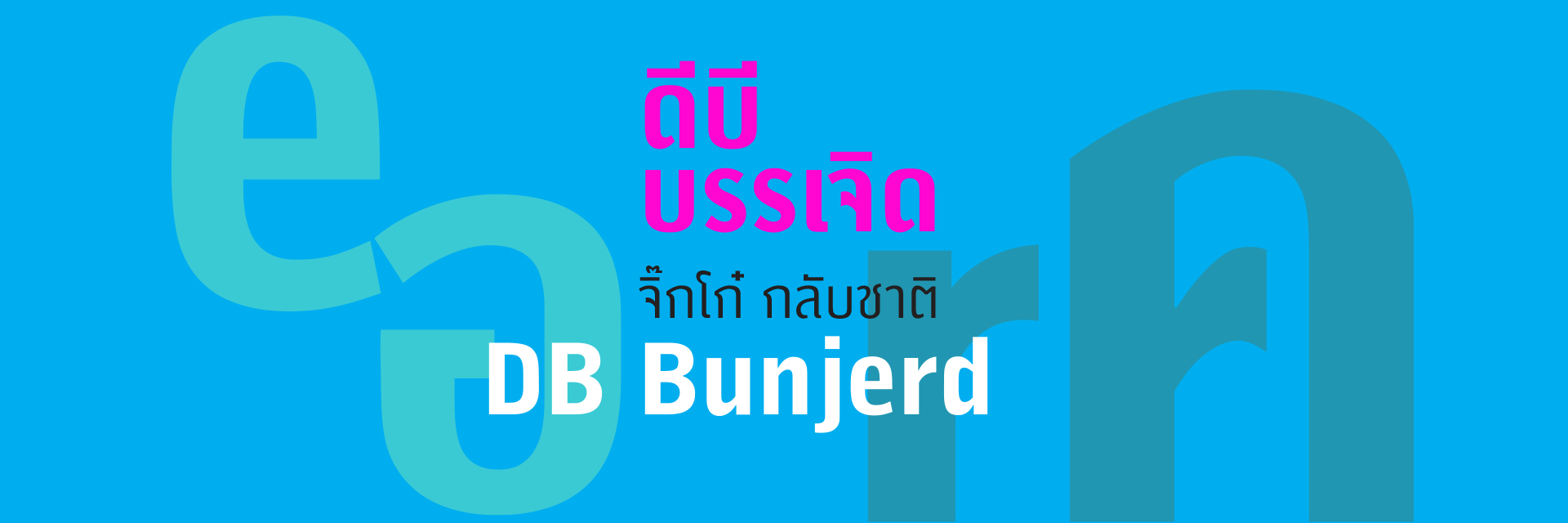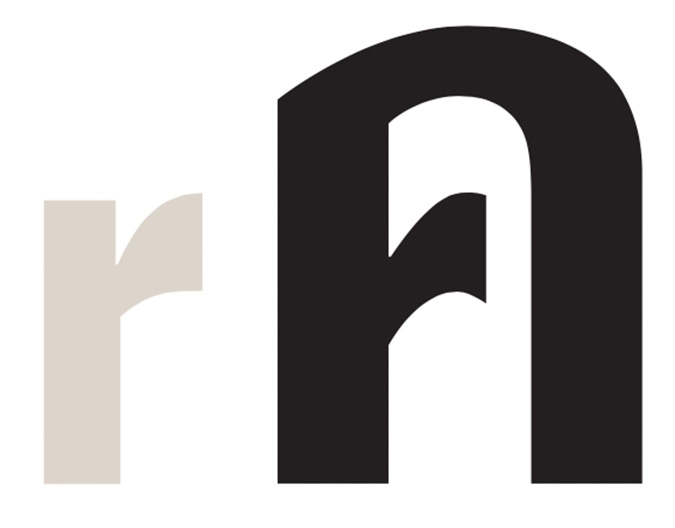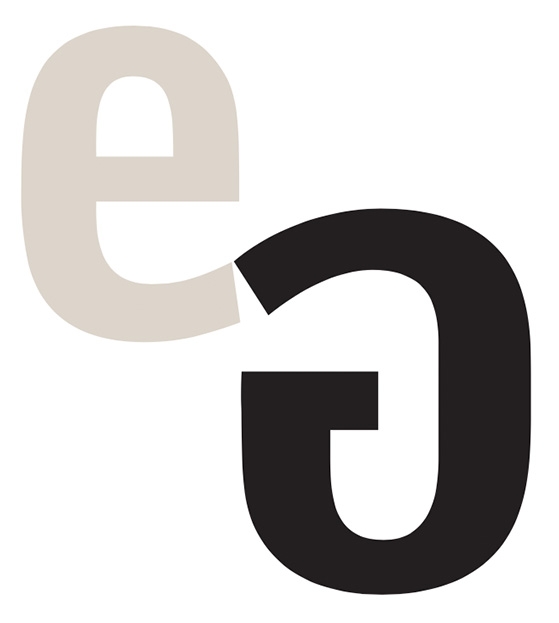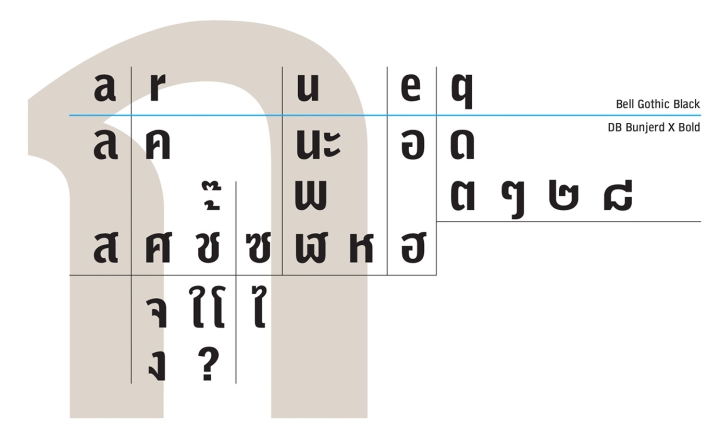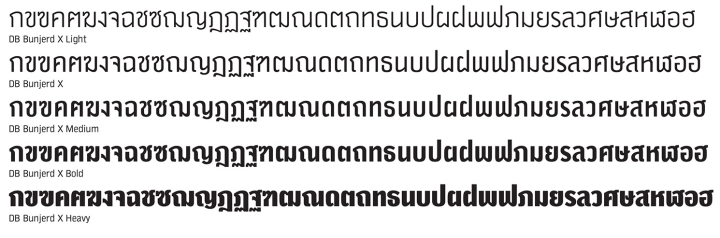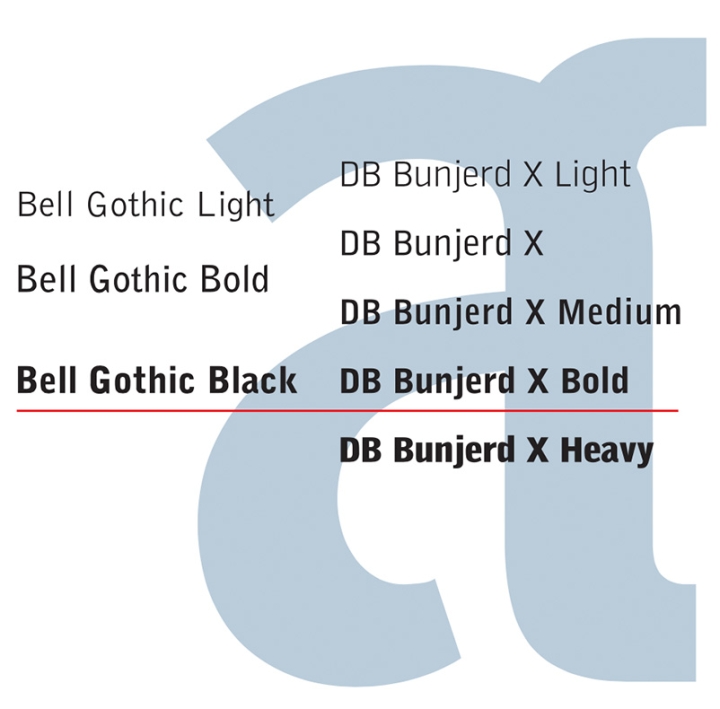
ถ้าใครมี American telephone directories ของปี ค.ศ.1937 อยู่ในมือ เปิดดูจะพบ ‘Bell Gothic’ ตัวพิมพ์ใหม่ล่าสุด (ของยุคนั้น) ที่ Chauncey H. Griffith ออกแบบ. ลักษณะเป็นตัวพิมพ์ที่อักษรค่อนข้างผอม เพื่อให้จุเนื้อหาได้มากๆ นั่นเอง. ทว่ารายละเอียดของรูปอักษรและช่องไฟหลวมๆ มีส่วนช่วยให้มันอ่านง่ายอย่างน่าทึ่ง.
ด้วยคุณความดีของ Griffith ทําให้ Bell Gothic กลับมาได้รับความนิยมอีกในยุค 1990s จนถึงปัจจุบัน Bell Gothic ที่ได้รับการอนุรักษ์เป็นฟอนต์ Opentype ล่าสุดนี้น่าจะยังคงเค้าโครงของเดิมของ Griffith อยู่มาก ดังจะเห็นได้จากน้ําหนักทั้ง Light และ Bold ของมันที่ค่อนข้างบางเมื่อเทียบกับฟอนต์ตัวเนื้อเรื่อง (text type) ที่เกิดใหม่ในยุคนี้. คงเป็นเพราะเดิมถูกออกแบบเป็นตัวเรียงพิมพ์ขนาดเล็กๆ ที่ต้องใช้พิมพ์บนกระดาษ ไม่เคลือบผิว (uncoated paper) จึงต้องทําเส้นบางเข้าไว้ (เพื่อซึมแล้วสวยพอดี!). ตัว Black ของ Bell Gothic ก็เช่นกันไม่ค่อยหนานัก เป็นได้แค่ Medium หรือ Bold ของฟอนต์แบบ sans serif ทั่วๆ ไปเท่านั้น.
Time to try? นิตยสาร art4d ใช้ Bell Gothic Black พาดหัวได้สวยมาช้านาน. ถึงเวลาหรือยังที่จะลอง “พูดไทย” ด้วย display ไทยที่เข้ากัน?
ที่น่าสังเกตเกี่ยวกับรูปอักษรของ Bell Gothic ทั้ง 3 น้ําหนักคือ ในชุด Light และ Bold จะมีส่วนคล้ายกันมากกว่า ส่วน Black จะแตกต่างออกไปอย่างเห็นได้ชัด กล่าวคือ ชุด Light และ Bold นั้น พวก ascender (หางของ b, d, h, k, l) จะตัดปลายทะแยงจากซ้ายขึ้นขวาเหมือนกัน ส่วนชุด Black จะตัดในแนวนอน. และเส้นแนวตั้งของอักษรทรงรีอย่าง c, e, o เส้นหน้าของ d, g, q หรือเส้นหลัง b, p ในชุด Light และ Bold ยังคงโค้ง ส่วนของชุด Black กลับ ถูกบีบเส้นตั้งให้ตรงมากน้อยต่างกันไป ในสายตาของผมแล้ว ผมกลับเห็นว่า Bell Gothic Black ดูเท่กว่าเพื่อนร่วมก๊วนของมัน. ถ้าเอามาเทียบกับ Meta (ที่กลายมาเป็น DB Moment) ฟอนต์ทรงค่อนข้างผอมเหมือนกันก็นับว่าต่างกันมาก. Meta ดูละเมียดละไมละเอียดทุกฝีก้าว พูดจาเสนาะหู ขณะที่ Bell Gothic ดูเรียบง่ายตรงไปตรงมาไม่อ้อมค้อม ทว่าสุภาพมีเสน่ห์ไม่ก้าวร้าวซึ่งเป็นบุคลิกที่ยังไม่เคยมีในฟอนต์ตระกูล DB. ยิ่งพิจารณาดูตัว u, n ของมันยิ่งเห็นความเหมาะสมจะนํามาเป็นต้นแบบทําตัวหัวเรื่อง (display) หรือหัวรอง (subhead) ไทย เพราะเส้นหน้าหลังเชื่อมโยงกันด้วยเส้นโค้งทะแยงสูง ทําให้นํามาปรับเป็นตัว น ที่ดูไม่สับสนกับ ม (ตัวกลับด้านของ น), บ และได้ ท ที่ไม่ดูสับสนเป็น ก ง่ายๆ (เมื่อใช้ในขนาดเล็กๆ หรือต้องดูไกลๆ) เหมือนที่เคยเกิดปัญหาจากฟอนต์ไทยเสมือนโรมันอื่นๆ.
การออกแบบตัวพิมพ์ไทยเริ่มต้นจากน้ําหนัก Bold ไทยก่อน โดยเทียบเคียงจาก Bell Gothic Black ต้นแบบ. ลักษณะเด่นของชุด Black นอกจากรูปอักษรทั้งชุดจะเป็นเส้นหนัก-เบาตามแนวตั้ง-นอนแล้ว ที่สําคัญคือ ตัวพิมพ์เล็ก (ซึ่งมักเป็นต้นแบบหลักในการปรับปรุงเป็นตัวพยัญชนะไทย) จะเน้นเส้นแนวตั้งให้ตรงเป็นพิเศษ. ดังนั้นตัว อ ที่ปรกติเส้นหน้าและเส้นหลังที่เคยโค้งก็จะถูกเหยียดตรงเหมือน e ของชุด Black. และตัว ด, ต จะมีเส้นหน้าตรงเหมือนตัว q เป็นต้น. ตัว ย ซึ่งมีที่ใช้ร่วมกับตัว อ บ่อยๆ จึงถูกซ่อนเส้นตรงสั้นๆ ในเส้นโค้งแนวตั้งเข้าไปด้วยให้ดูกลมกลืนกัน
ตัว ก ซึ่งแม้จะดูตรงๆ อยู่แล้ว ส่วนปลายปากก็ยังจงใจตัดตรงในแนวตั้ง. หางของ ฎ ฏ ที่มักเคยชินกับการจบด้วยเส้นโค้งหรือเส้นตรงแนวทะแยงที่ส่วนปลาย กลับเลือกจบด้วยเส้นตรงสั้นๆ ในแนวดิ่งแทน
สระอะ ที่แม้จะมีหางโค้งทะแยงก็ยังคงรูปหัวเส้นตรงสั้นๆ ในแนวดิ่งเอาไว้ (ไม่ใช้ลักษณะนี้กับไม้หันอากาศ เพราะจะดูสับสนกับไม้โทเอาได้!) หางโค้งทะแยงของ ะ เป็นความจงใจให้สัมพันธ์กับเส้นล่างของตัว น ที่ได้จาก u ของชุด Black. หยักที่ฐานของ พ, ฟ ก็ได้จากการเลียน แบบเส้นล่างของ น เช่นกัน
ตัว ข แม้ว่าส่วนหัวยังคงขมวดม้วนขนาดใหญ่ล้ำเส้นหน้าออกไปให้อ่านได้ชัด (ตามแบบฉบับของ DB) แต่เลือกชนกับเส้นดิ่งให้เห็นเป็นสันโดยไม่ลบมุมเพื่อเปิดโอกาสให้เห็นแนวเส้นตรงได้ยาวขึ้น
บ่อยครั้งที่เราจะพบความสับสนระหว่างตัว ซ กับ ช ในตัวพิมพ์ขนาดเล็กๆ หัว ซ ที่ได้จากการเติมขีดสั้นๆ ในแนวดิ่งก่อนขมวดหัว นอกจากจะเป็นการรักษา DNA ของตัวพิมพ์ชุดนี้แล้วยังช่วยแก้ปัญหาความสับสนกับ ช อย่างได้ผลชะงัด. ลักษณะหัวของ ซ ตกทอดไปถึงตัว  ไ รูปโฉมแปลกตา. ส่วน ใ และ โ เป็นไปในทํานองเดียวกับหัว ข, ช เช่นเดียวกับเครื่องหมายคําถาม ที่ต่างไปจากของชุด Black เดิมของ Griffith.
ถ้าสังเกตเส้นบนของตัว ต ตรงรอยหยักให้ดีจะพบ ว่าต่างไปจาก q ต้นแบบ คือ แทนที่เส้นหลังจะตรงที่อ กลับปรับให้ปลายบนดูคล้ายเลข 1 ซ่อนอยู่เพื่อเน้นรอยหยักขึ้นให้ดูเป็น ต ได้ง่ายขึ้น. ลักษณะพิเศษนี้ถูกใช้ต่อในหลายที่ คือ ผ, ฝ, ๆ, ๒, ๘ และไม้ไต่คู้.
แม้สัดส่วนตัวพยัญชนะปรกติอย่าง น, บ จะกว้างกว่า ตัว u ของ Bell Gothic Black เล็กน้อย แต่เมื่อถึงบทตัวที่ควรผอมได้ เช่น ง, จ, ว ก็เลือกที่จะผอมเป็นพิเศษเพื่อใช้ความแตกต่างของความกว้างรูปอักษรให้เกิดประโยชน์ในการอ่าน, หางตัว ง, หัวตัว จ (เช่นเดียวกับหัวตัว ค) ยืมมาจากหางตัว r แตะกับเส้นตั้ง จะได้ดูผอมๆ โล่งๆ เหมือนตัว r สมใจอยาก. อักษรตัวแคบพวกนี้จะมีชุดสระ อิ อี อึ อื ชุดแคบของมันเอง เพราะได้ทํา ligature ไว้ให้แล้ว (ต้องใช้กับโปรแกรมที่รองรับ ligature ได้เท่านั้น) จึงไม่ต้องกลัวสระบนของมันจะไปชนทับหาง ป, ฝ, ฟ หรือสระบนของตัวพยัญชนะที่อยู่ข้างหน้า.
ตัว ล เส้นหลังของมันยังคงปลายล่างงอเล็กน้อยแบบ ตัว a ต้บแบบไว้เพื่อแก้เลี่ยน. หาง ส ที่งอกลักษณะล้อเลียนกับปลายล่างของมัน ถูกนําไปใช้กับหาง ช, ซ, ศ. ฬ, ฮ และเลยเถิดไปถึงขมวดม้วนของ ห ทําให้ได้ ห ที่ดูแปลกตาออกไปจากเดิมๆ.
ในรายละเอียดเล็กๆ น้อยๆ เช่นการเล่นสันที่รอยต่อระหว่างเส้นตั้งด้านหน้ากับเส้นโค้งบนในตัว ค, หัวของไม้โท ที่คล้ายหัว ข รวมทั้งไม้ตรีที่งอกเงยออกมาจากไม้โท ฯลฯ ทําให้แบบตัวพิมพ์ไทยใหม่ที่ได้ชุดนี้ดูมีบุคลิกชัดเจนเป็นของมันเอง. จะมีอักษรบางตัวเท่านั้นที่อาจดูไม่แตกต่างจากฟอนต์อื่นๆ เช่น บ, ป หรือสระ า เป็นต้น (รวมเป็น ‘บาป’ พอดี!).
ส่วนพวกสระบนล่างทั้งหมด รวมไม้เอก, ไม้จัตวา, การันต์ ถึงจะปล่อยให้มันดูคล้ายๆ กับฟอนต์อื่นไปบ้าง ก็ไม่มีผลต่อบุคลิกตัวพิมพ์ชุดนี้เท่าใดนักเพราะมันไม่สามารถใช้โดดๆ ได้ ต้องผสมกับตัวพยัญชนะซึ่งส่วนใหญ่มีบุคลิกชัดเจนอยู่แล้ว.
เมื่อเสร็จน้ําหนัก Bold ของภาษาไทยและปรับแต่ง Bell Gothic Black ให้กลมกลืนเข้าชุดกันแล้วจึงขยายครอบครัวออกไปเป็น Medium, Regular, Light และตบท้าย ด้วย Heavy ให้สะใจขึ้นไปอีกรวมเป็น 5 น้ําหนัก (แซง Bell Gothic เดิมที่มีอยู่เพียง 3 น้ําหนัก) เนื่องจากน้ําหนักเส้นของชุดที่เพิ่มเติมขึ้นมาไม่ซ้ำกับน้ําหนักเดิมเลยและรูปลักษณ์อักษรยังแปลกตาออกไป จึงไม่เป็นการเกินเลยไป สําหรับการให้ชื่อฟอนต์ 5 น้ําหนัก รวมกับตัวเอนเป็น 10 สไตล์ชุดนี้ว่า ‘DB Bunjerd’
คําศัพท์เก่าอย่าง ‘บรรเจิด’ ยังกลับมาฮิตในกลุ่มคนรุ่นใหม่ได้ ทําไม DB Bunjerd เหลนของเจ้าคุณทวด Bell Gothic จะกลับมาบรรเจิดไม่ได้!